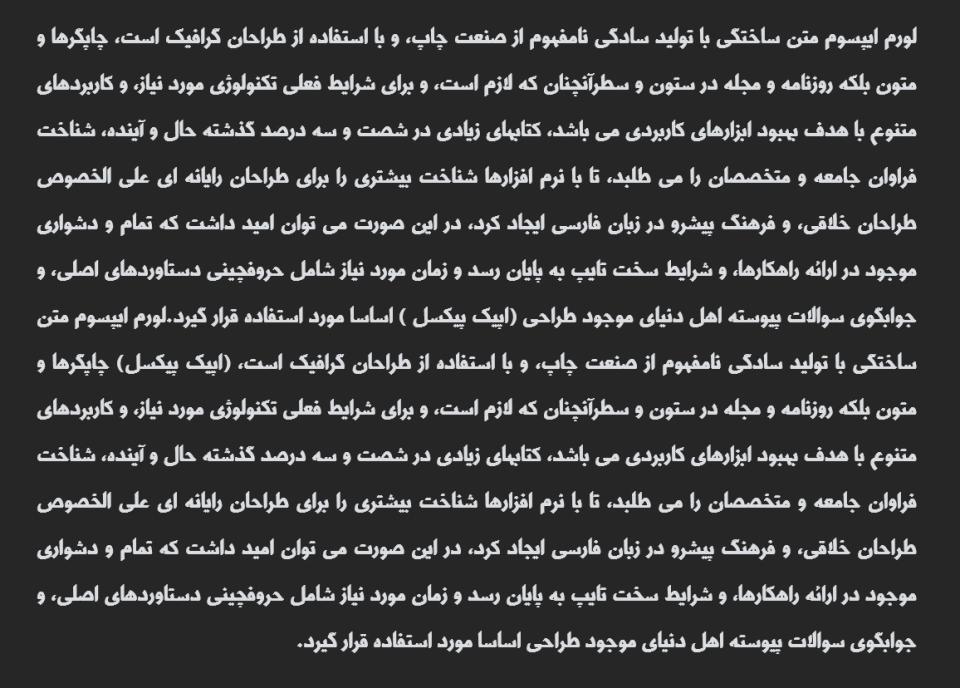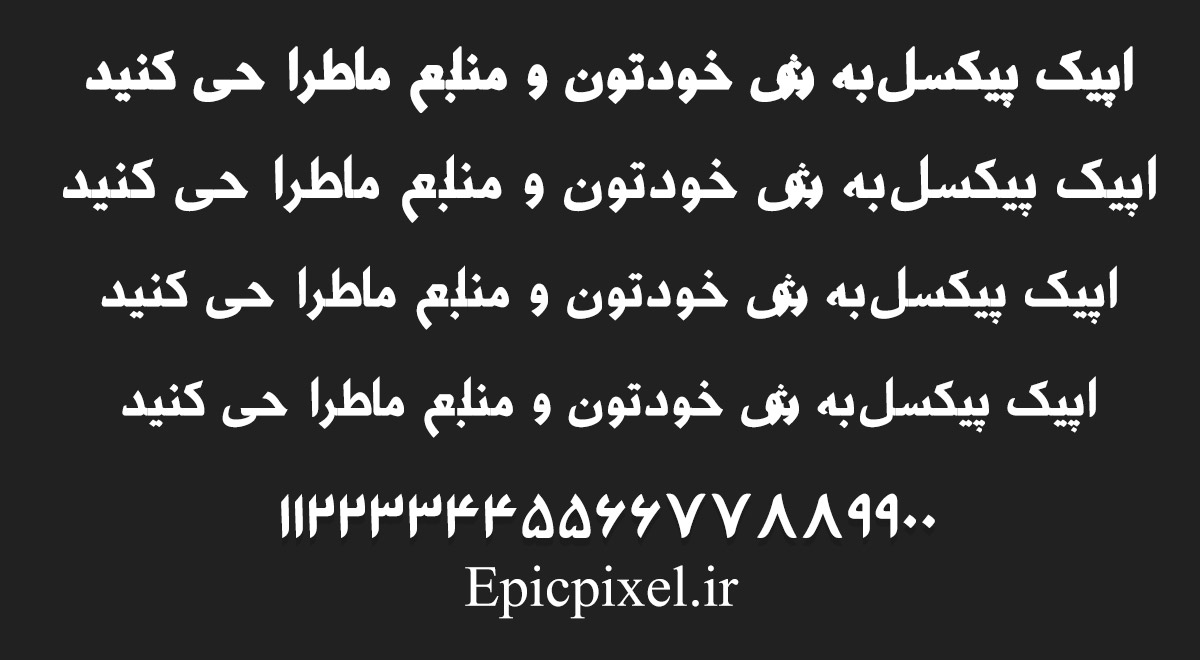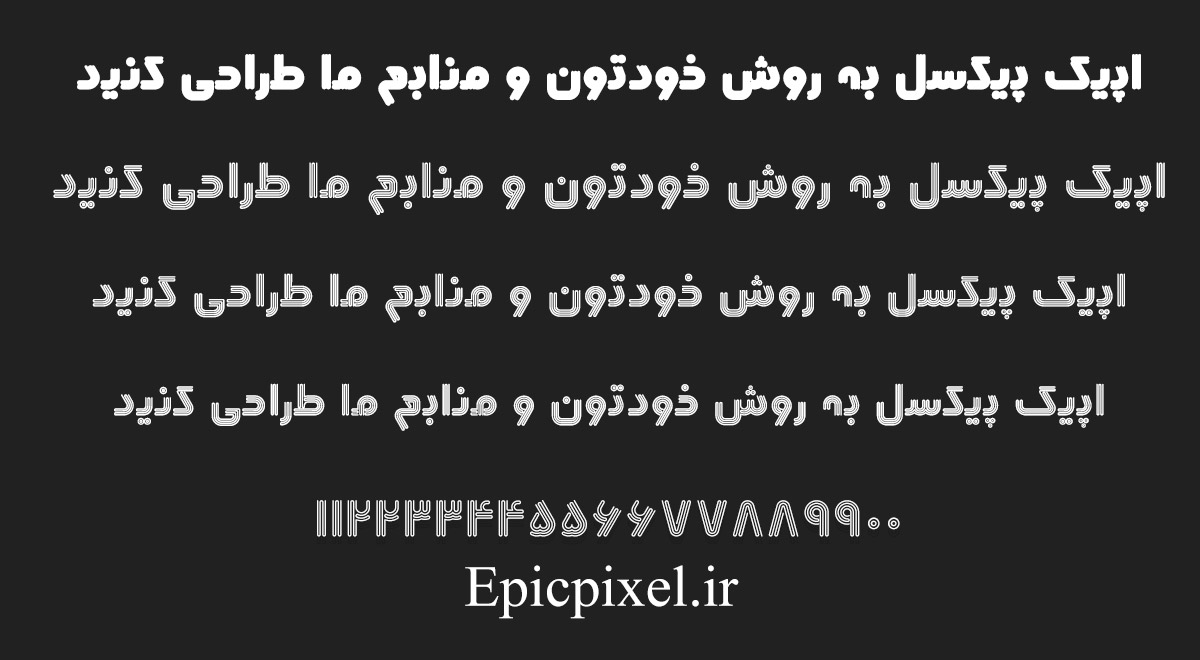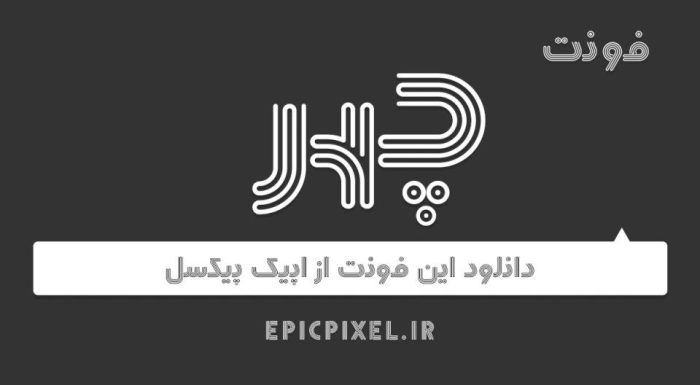
2 فونت چهر فارسی Chehr
فونت چهر فارسی، با طراحی منحصربه فردش، جان تازه ای به نوشته های شما می بخشد. این فونت، با ساختار هندسی دقیق حروف و خطوط نرم و دلنشین، خوانایی بالایی را هم در متن های طولانی و هم در عناوین کوتاه ارائه می دهد. اگر به دنبال فونتی هستید که هم در طراحی های مدرن و هم در پروژه های سنتی تر به خوبی بنشیند، چهر انتخابی ایده آل است.
یکی از ویژگی های برجسته این فونت، تنوع وزن های آن است که به شما اجازه می دهد در هر موقعیتی، وزن مناسب را انتخاب کنید. از وزن بسیار نازک برای ظرافت بیشتر گرفته تا وزن ضخیم برای تأکید و برجسته سازی، چهر انعطاف پذیری بالایی را در اختیار شما قرار می دهد. این تنوع وزن ها به خصوص برای طراحان گرافیک و صفحه آراها که به دنبال کنترل دقیق بر ظاهر متن هستند، بسیار ارزشمند است.
فونت چهر، با وجود ظاهر مدرنش، ریشه های خود را در خوشنویسی اصیل فارسی حفظ کرده است. این ترکیب هوشمندانه از سنت و مدرنیته، به چهر هویتی خاص بخشیده که آن را از سایر فونت ها متمایز می کند. با این حال، باید توجه داشت که به دلیل طراحی خاص برخی حروف، ممکن است در اندازه های بسیار کوچک، کمی از خوانایی آن کاسته شود که البته در اکثر موارد چاپی و دیجیتال، این مسئله چندان به چشم نمی آید.
فونت عالی هست شبیه ابتکاره ولی خیلی پرو تره…